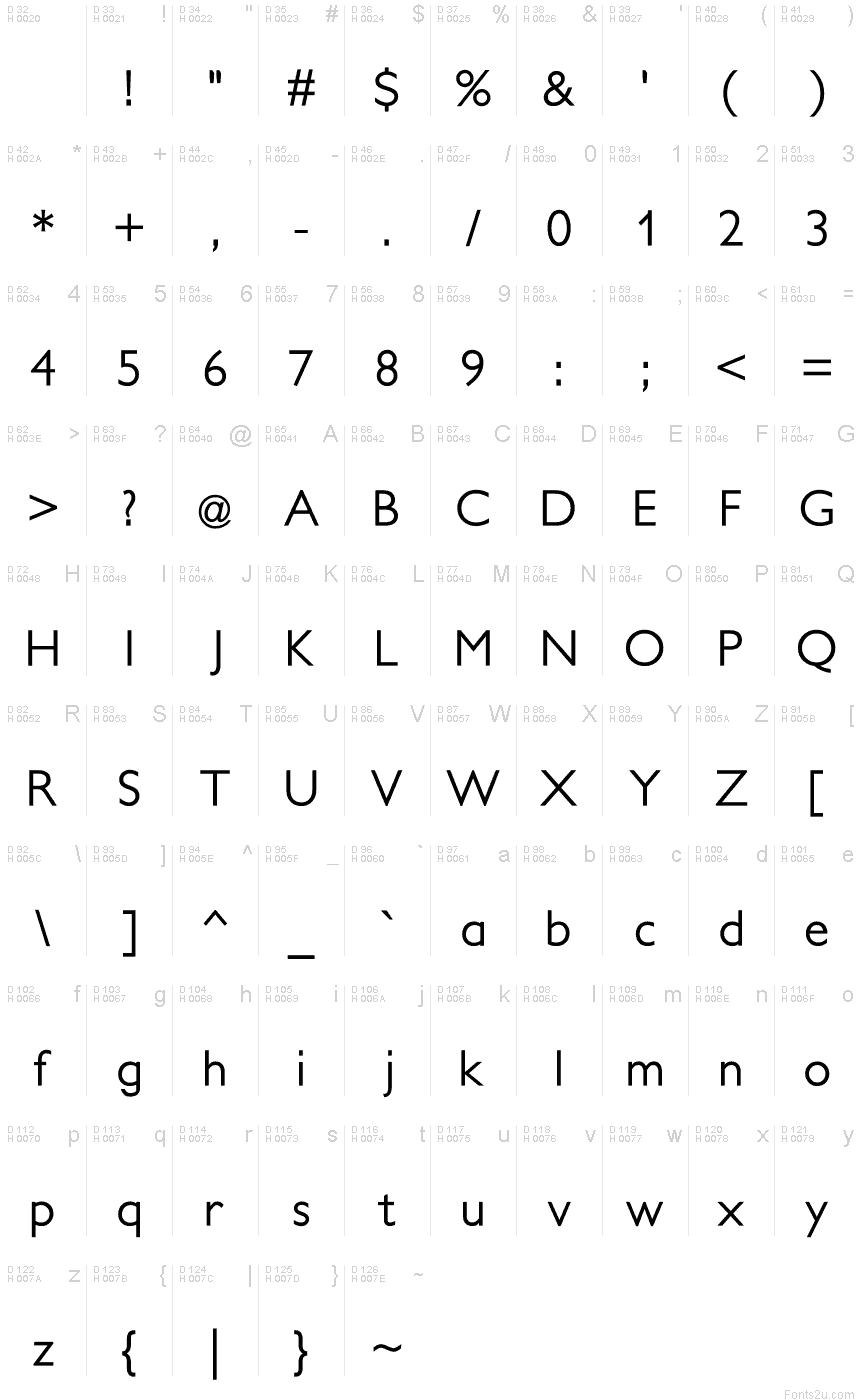
PetitaMedium
Petita Medium od M. Klein je bezplatné geometrické bezpatkové písmo s klidným, střídmým rytmem. Písmena těží ze širokých kruhových tvarů a rovných, vyvážených tahů, což mu dodává jemný modernistický nádech, který působí jednoduše, nikoliv stroze.
Díky tomu je přirozenou volbou pro identitu značek, obálky knih, obaly, plakáty a redakční titulky, kde je žádoucí decentní grafický projev. Jako bezplatný font se skvěle hodí pro krátké nadpisy, logotypy a titulní karty, protože kulaté tvary a otevřené rozestupy udržují písmo přátelské, a přitom stále působí uceleně.